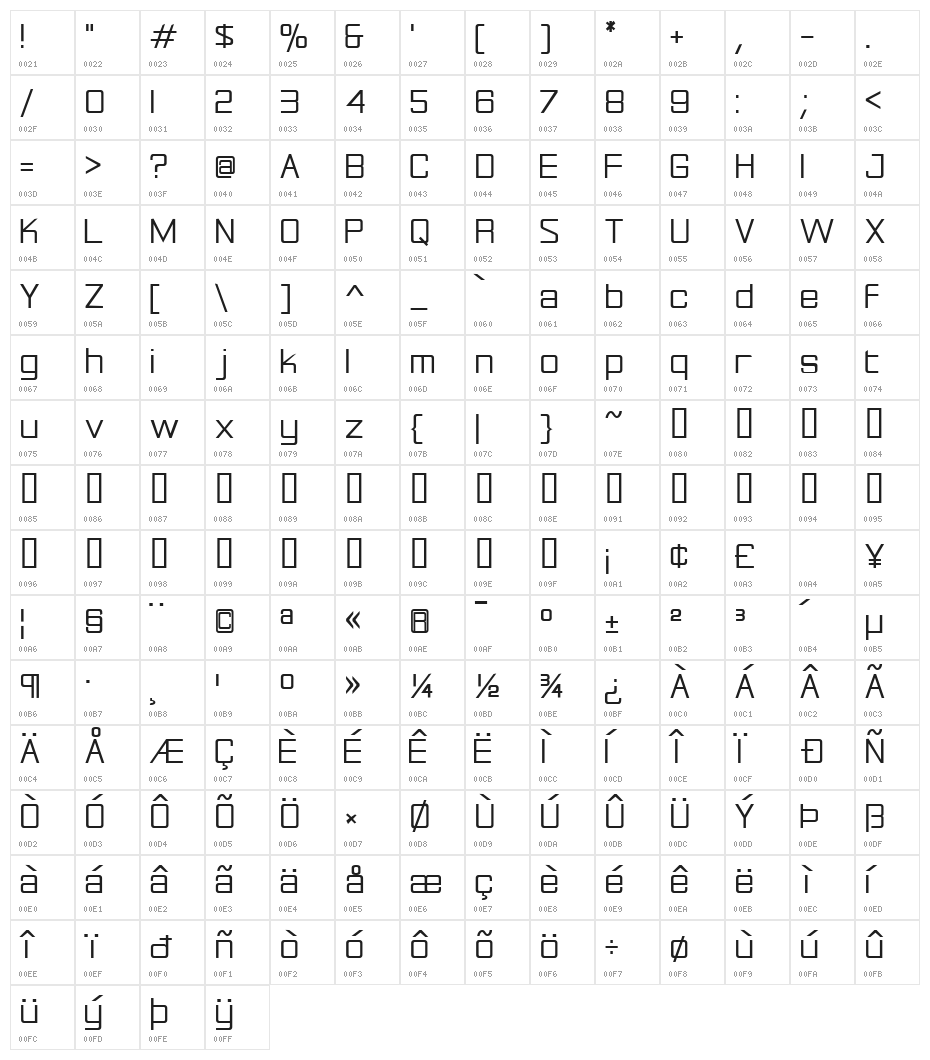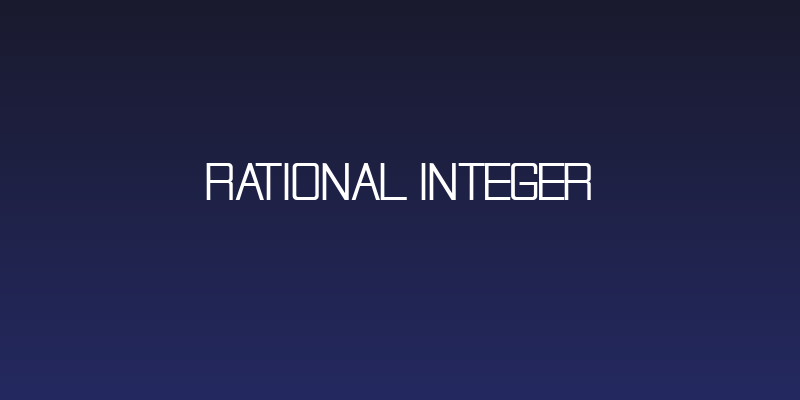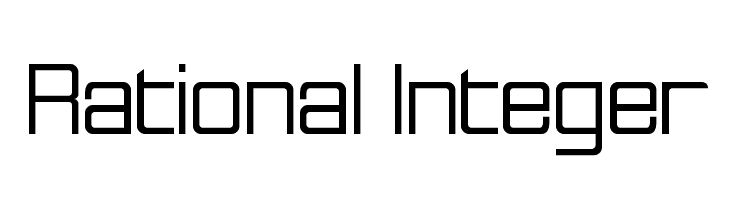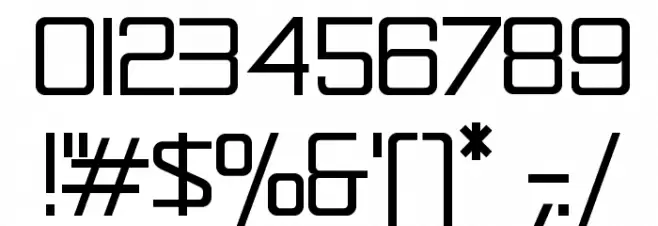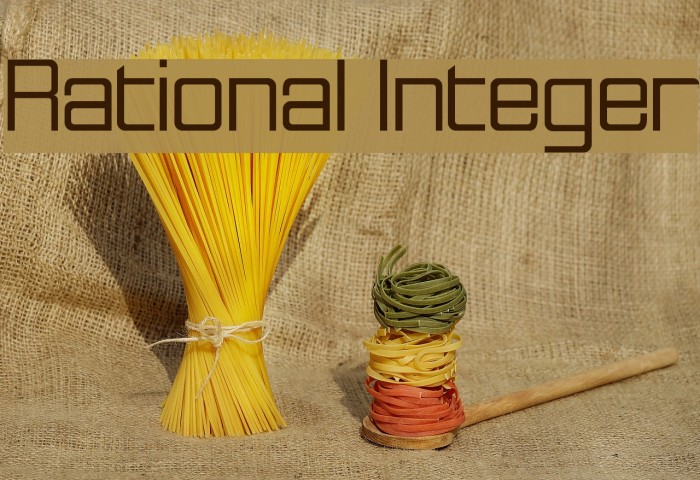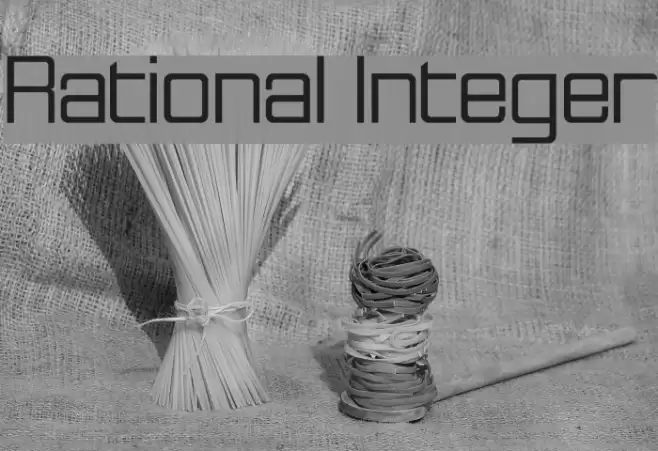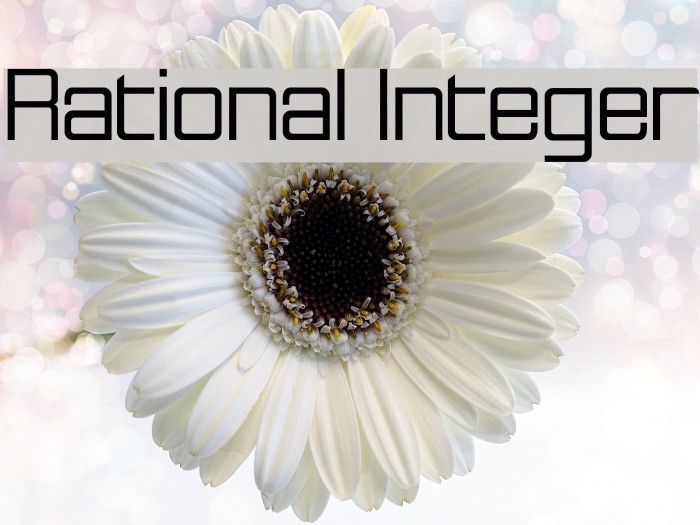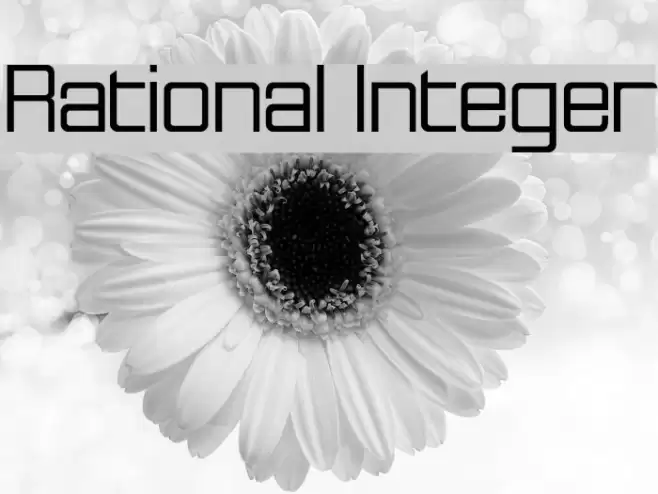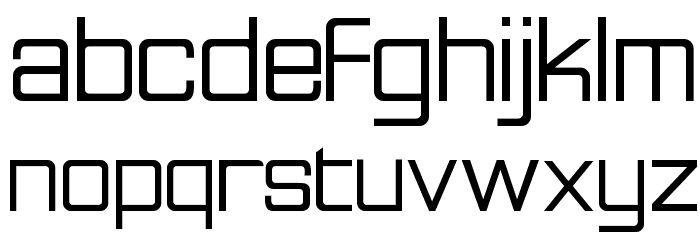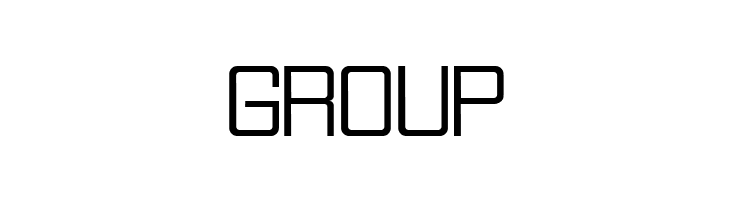
Rational Integer Font
| Cas d'utilisation | Headlines, Logos, Digital interfaces |
| Projets proposés | Ideal for tech branding, modern web design, digital interfaces, and minimalist print materials. |